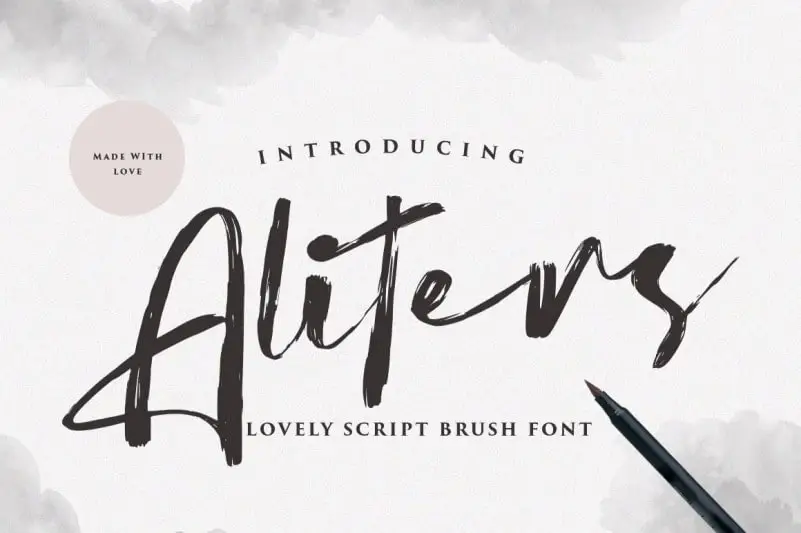
Aliters Brush Font – Fonte Grátis
Aliters Brush Font
A Aliters Brush Font é uma elegante tipografia feita especialmente para designers que buscam adicionar um toque único e criativo às suas criações digitais. Sua origem está no design de vultype, uma mistura sofisticada entre escrita a mão e fonte com canetinha, projetada para se adaptar perfeitamente à sua necessidade de criar designs que chamem atenção. Esta fonte script foi desenvolvida em parceria com um único pen capaz de capturar a essência do design artesanal. É tão versátil quanto a própria criatividade, permitindo que você desfrute da sua beleza incrivelmente diversificada e use-a para criar cartões de aniversário encantadores, arte de estação sofisticada, postagens sociais chamativas e muito mais. Esse é o tipo de fonte que cai na graça de qualquer designer em busca de dar um toque especial a seus trabalhos.